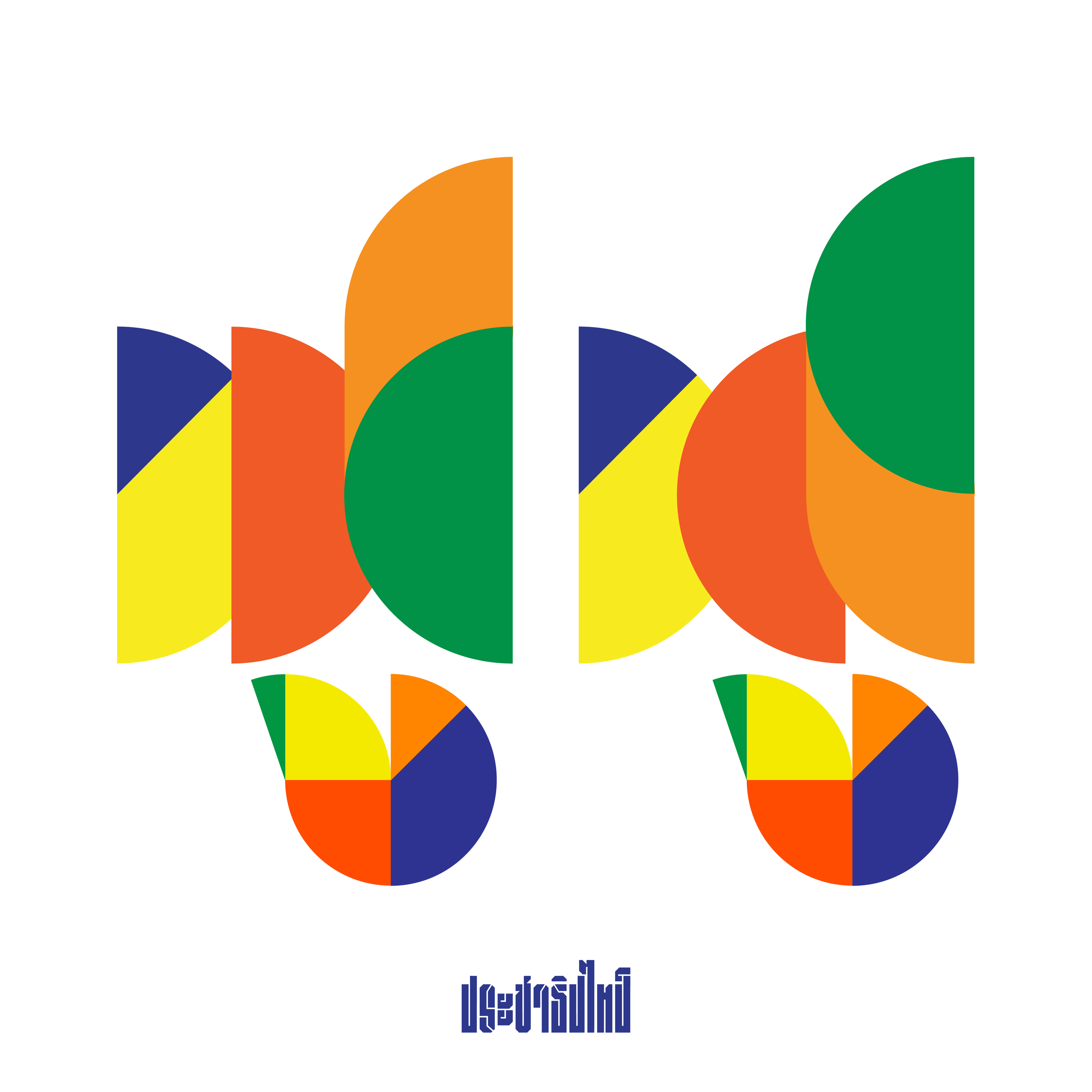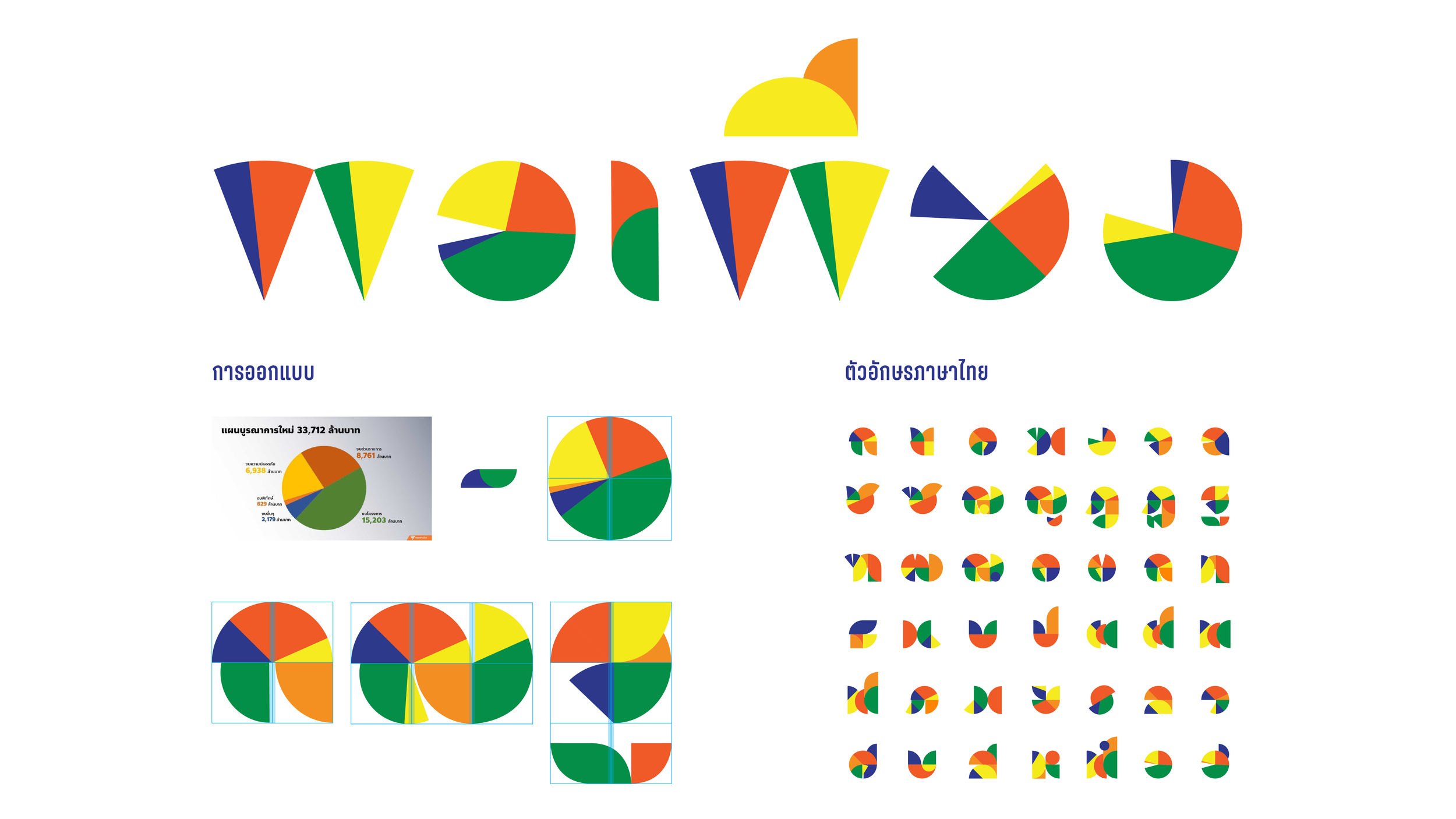
33712
ฟอนต์ที่ได้รับแรงบันดาลใจจากกราฟ #งบประมาณปี65 ในส่วนของสถาบันกษัตริย์ โดยส.ส.จากพรรคก้าวไกล
ท่ามกลางความยากลำบากของประชาชนที่ต้องเผชิญกับการระบาดของโรค COVID-19 และการบริหารจัดการที่ล้มเหลวของรัฐบาล เมื่อเราเห็นกราฟวงกลมดังกล่าวในข่าว จึงตัดสินใจนำรูปร่างของกราฟนั้นมาดัดแปลงเป็นคำว่า “พอเพียง” ซึ่งเป็นหลักปฏิบัติที่คอยยึดเหนี่ยวจิตใจของคนไทยเสมอมา
เมื่อภาพ “พอเพียง” ได้รับการตอบรับอย่างดีบนโซเชียลมีเดีย เรานั้นจึงขยายผลเป็นการออกแบบตัวอักษรไทยครบชุดโดยมีองค์ประกอบหลักเป็นชิ้นส่วนของวงกลม และชุดสีที่ปรับให้สดใสขึ้นจากกราฟต้นฉบับ
ชื่อฟอนต์ “33712” มาจากจำนวนเงิน 33,712 ล้านบาท ที่ถูกจัดสรรตาม “แผนบูรณาการใหม่” ดังที่ถูกนำเสนอในสไลด์ประกอบการอภิปราย
งบประมาณ
หลังจากเปิดตัวฟอนต์ 33712 ทางวง Rap Against Dictatorship ได้ส่งเพลง “งบประมาณ” มาให้ฟัง พร้อมกับชวนเราออกแบบปก
จากเนื้อหาของเพลงที่พูดถึงการจัดสรรและใช้จ่ายงบประมาณอย่างไม่เหมาะสมกับสถานการณ์ และไม่เห็นความสำคัญของชีวิตประชาชน เราจึงใช้ฟอนต์ 33712 เขียนคำว่า “งบประมาณ” ร่วมกับภาพประกอบที่ใช้โต๊ะหมู่บูชาสื่อถึงการจัดลำดับความสำคัญตามวัฒนธรรมไทย
เนื่องจากการระบาดของ COVID-19 ทำให้ทางวงไม่สามารถออกกองเพื่อถ่ายทำมิวสิควีดิโอได้ตามแผน เราจึงช่วยดูแลเรื่องการใช้ตัวอักษรใน lyrics video ให้ออกมาเป็นภาพที่สามารถแคปวรรคเด็ดไปแชร์ต่อได้สะดวก